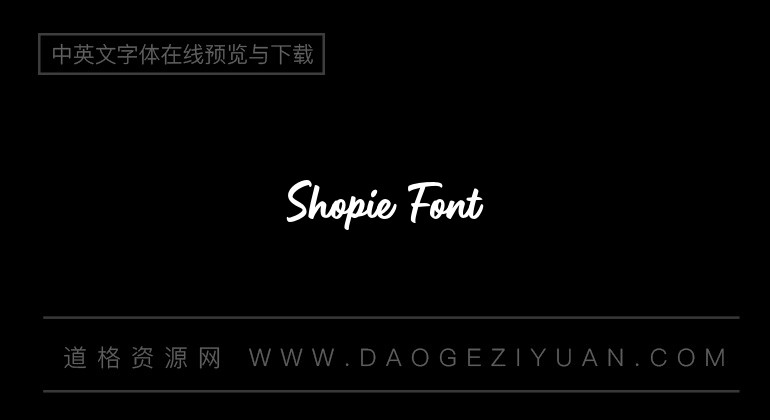
Shopie Font
Sophie Font 是一种非常流行的手写字体,其设计旨在使文本看起来像是手写的。Sophie Font 的特点是字母之间的连线和装饰,这使得它非常适合用于设计书信、个人卡片、海报、标志和其他类似的项目。 Sophie Font 包含大写字母、小写字母、数字和标点符号,而且它的字母形状很流畅,使得文本易于阅读。此外,Sophie Font 还有一些变体,其中包括一些装饰性的字母形式,这可以让文本看起来更加生动有趣。 Sophie Font 具有非常广泛的用途,可以用于设计项目、品牌标志、个人博客和社交媒体帖子等,特别是在需要突出文本的视觉效果时,Sophie Font 是一种非常好的选择。
Shopie Font是一款非常不错的手写艺术字体,具有很好的视觉感,适合于文化类的宣传设计、商业类品牌的广告和产品包装设计以及个性化文字排版等较多场景。